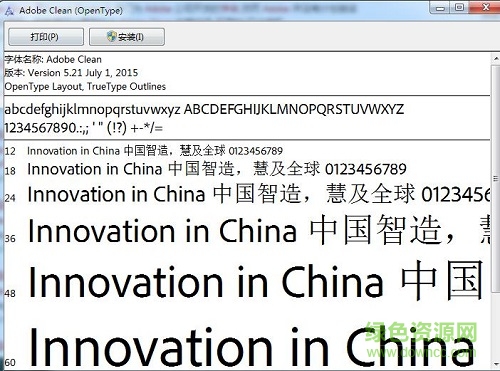
adobe clean字體是adobe公司專用字體,字形比劃圓潤,適用于廣告、藝術(shù)設(shè)計(jì),海報(bào)設(shè)計(jì)等方面,小編特意整理手機(jī)了所有的adobe clean字體,感興趣的朋友歡迎來綠色資源網(wǎng)免費(fèi)下載使用!
adobe clean字體是一款專為需要進(jìn)行設(shè)計(jì)的朋友準(zhǔn)備的電腦字體,字體看起來柔美,纖細(xì),如同柳枝輕撫書頁,看起來很舒心,適合內(nèi)文排版,手機(jī)系統(tǒng),內(nèi)嵌程序等應(yīng)用。